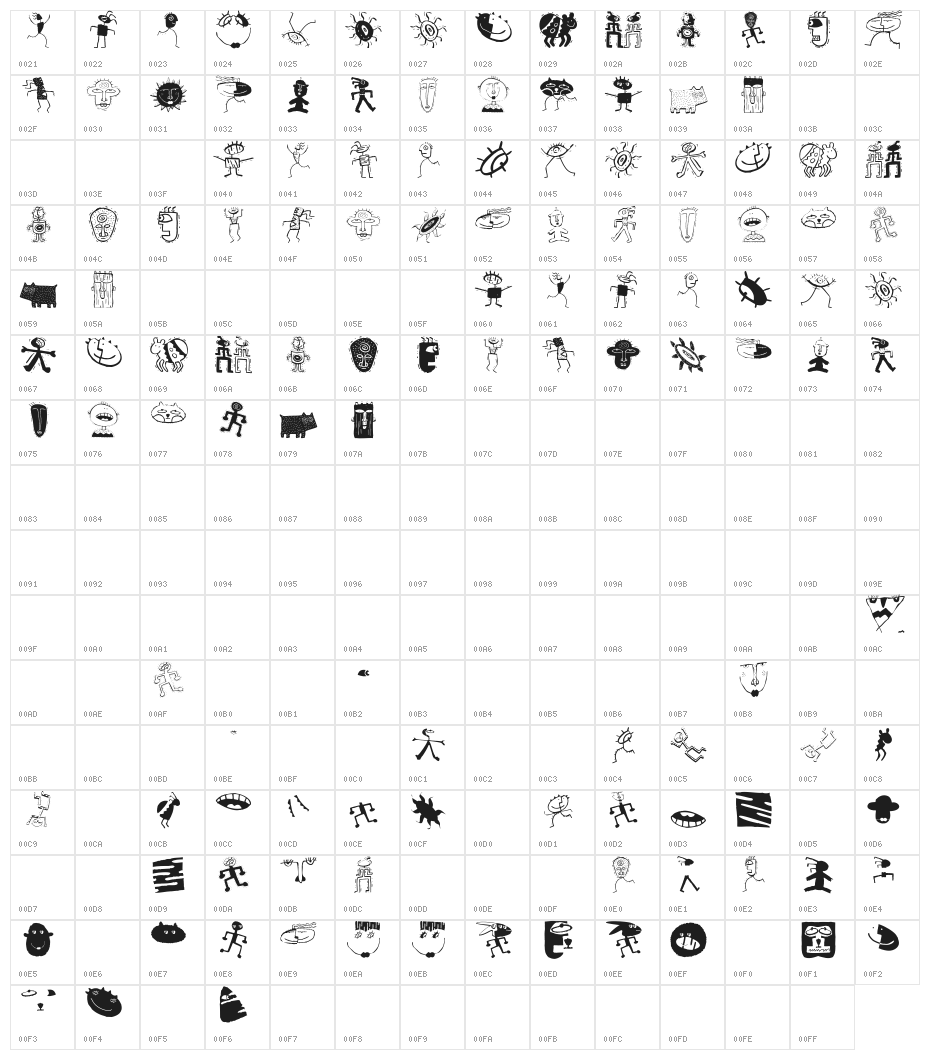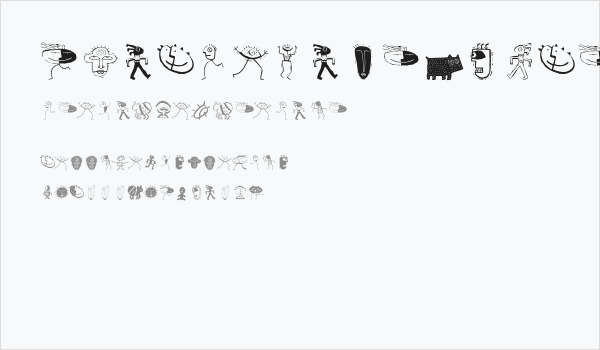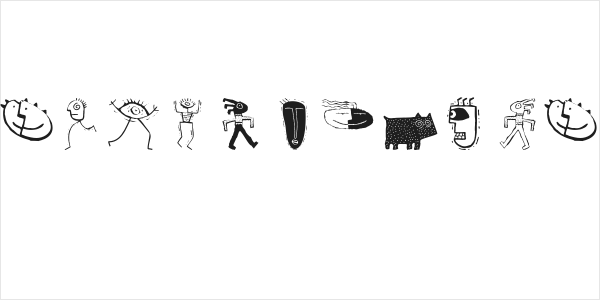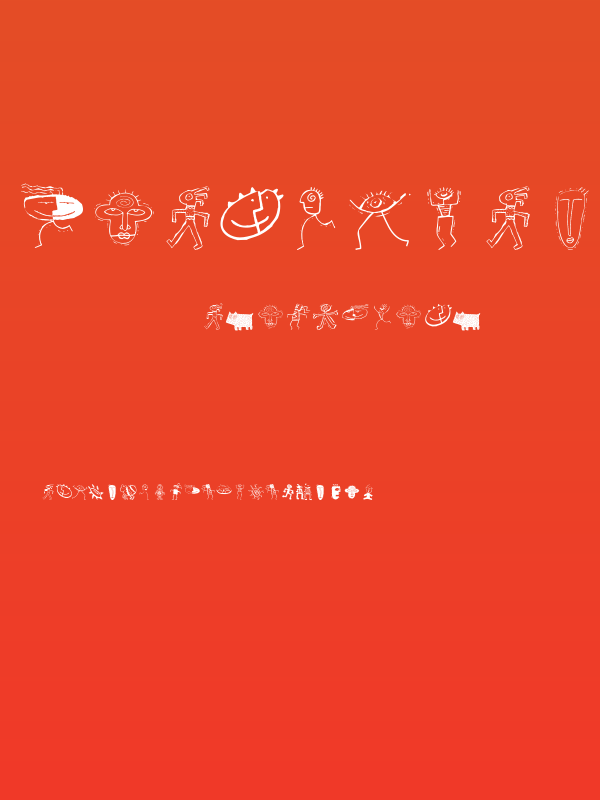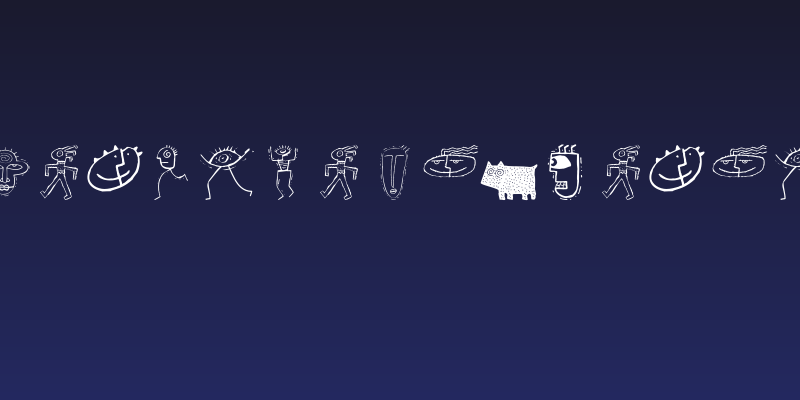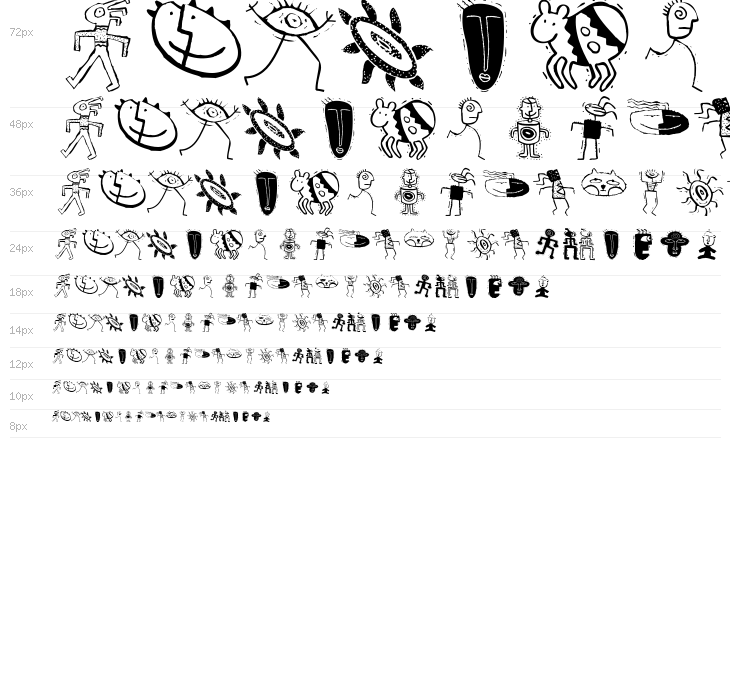
20thCentury-Three Font
✎ Dingbats
| 整体风格 | Modern, Artistic, Surreal |
| 使用场景 | Logos, Posters, Artistic Designs |
| 推荐项目 | Ideal for artistic projects, creative branding, unique posters, and any design work that seeks to incorporate a playful and imaginative aesthetic. |